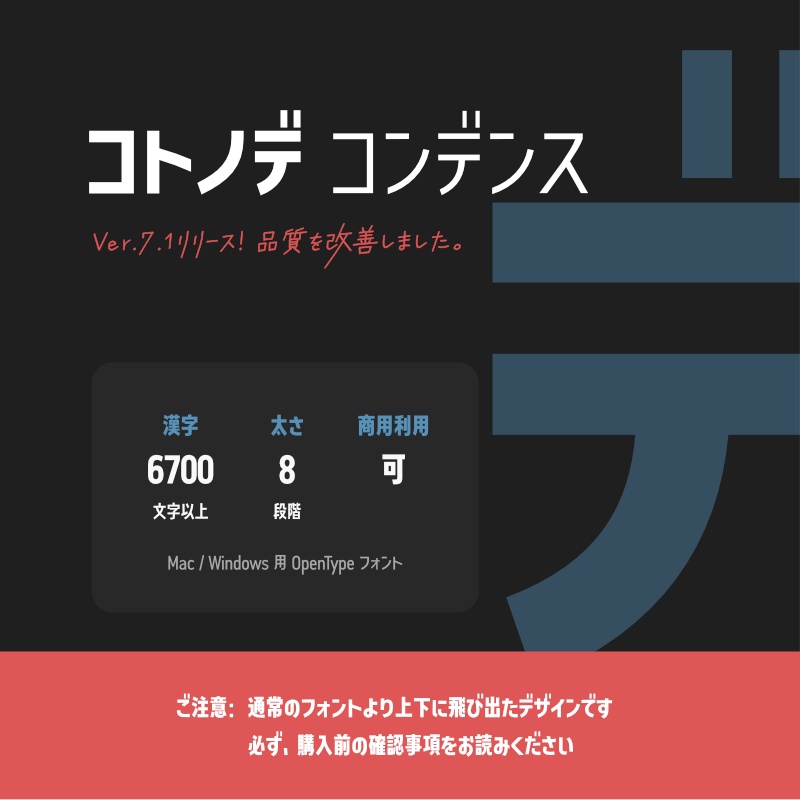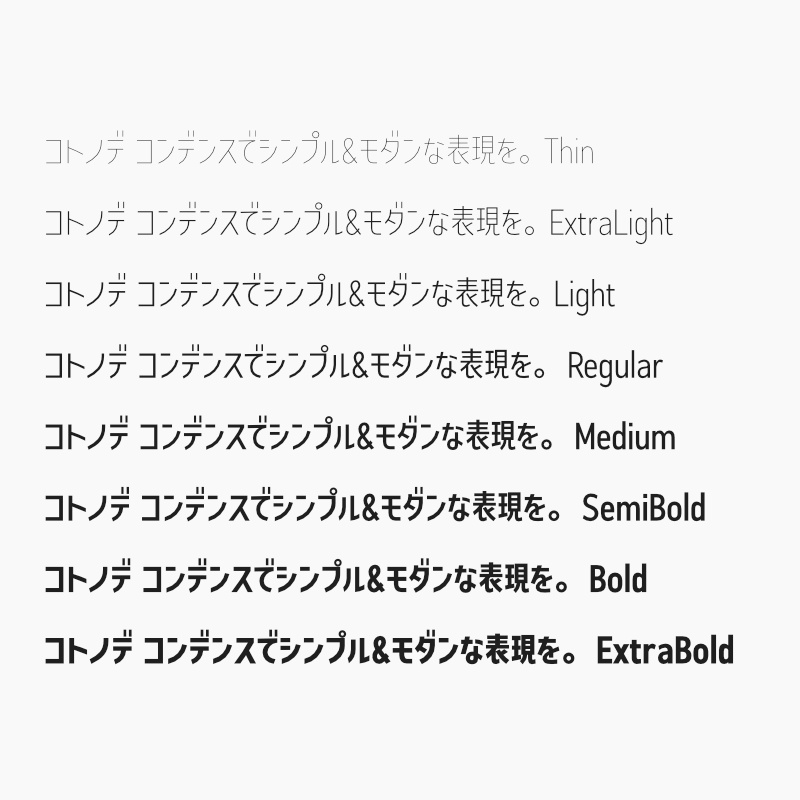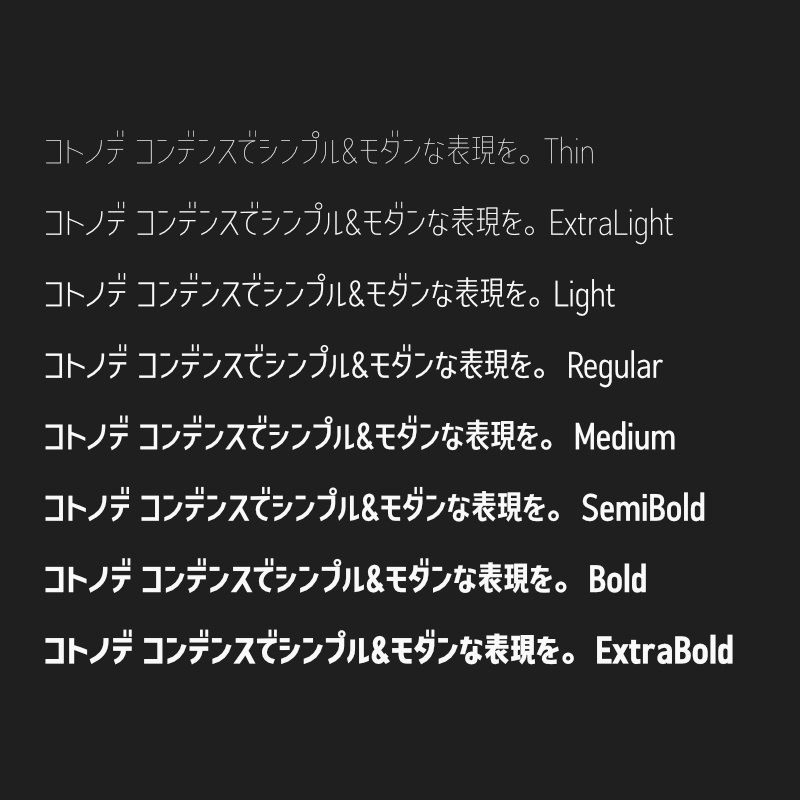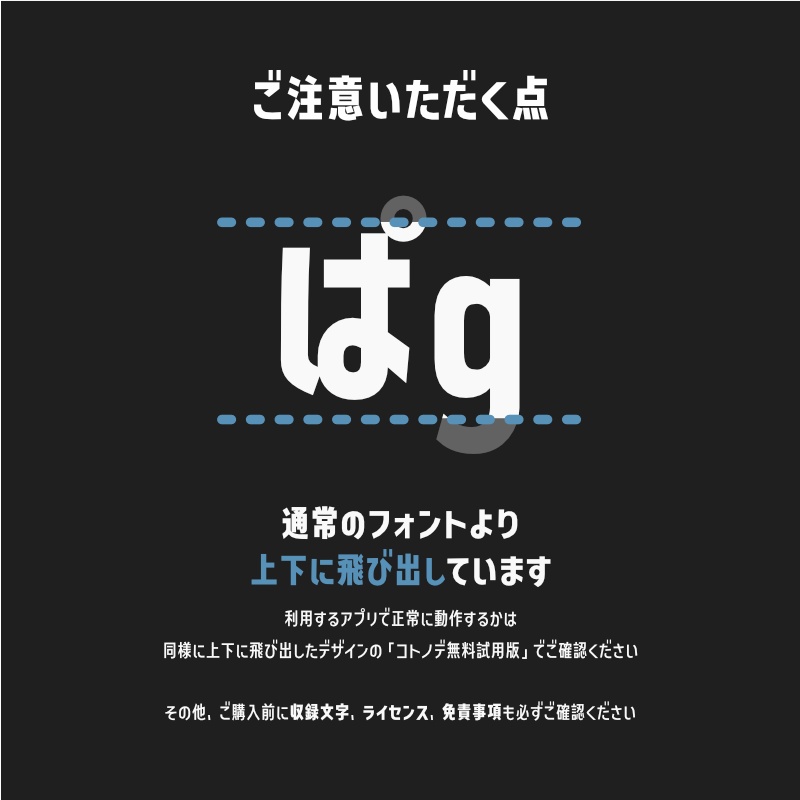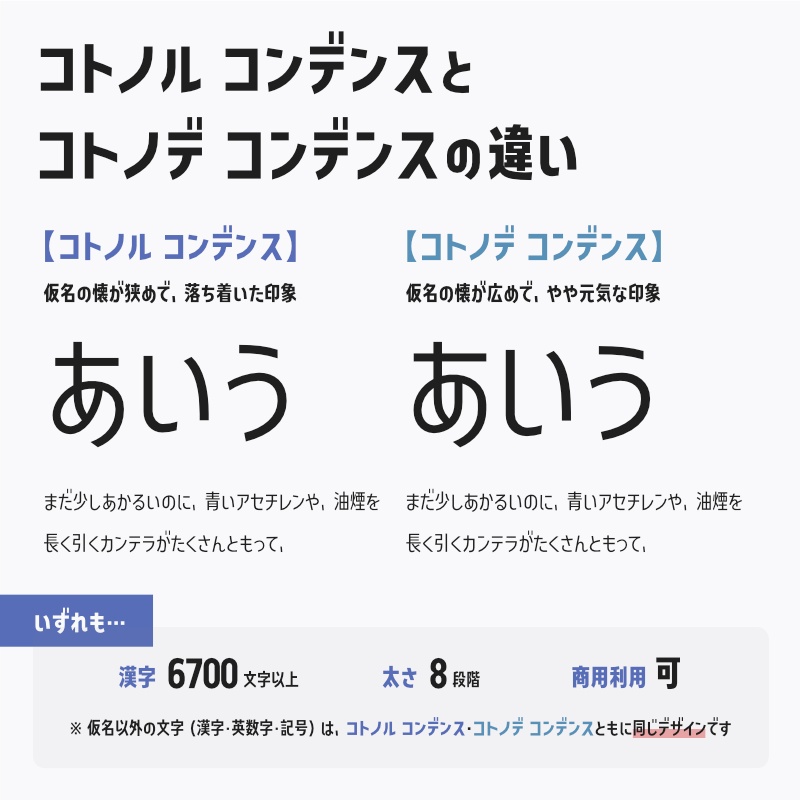
「コトノデ コンデンス」フォント(漢字あり) ~縦長で明るい雰囲気のゴシック体~
・通常のフォントよりも上下にはみ出たデザインです。ご利用のアプリによっては上下が見切れることがあります。ご購入前に確認したい場合は、同様に上下にはみ出たデザインの「コトノデ無料試用版(※)」をご活用ください。 ・漢字は6,700文字以上収録しており、常用漢字・JIS第一水準漢字・JIS第二水準漢字をカバーしています。収録文字は公式の紹介ページをご確認ください。 ・公式の紹介ページの利用規約・免責事項を必ず確認してください(商用利用可・再配布禁止)。 【公式の紹介ページ】 https://kotonohaworks.com/kotonode-condensed.html (※コトノデ無料試用版) https://dkf.booth.pm/items/2727320(無料試用版に漢字は含まれていません。)